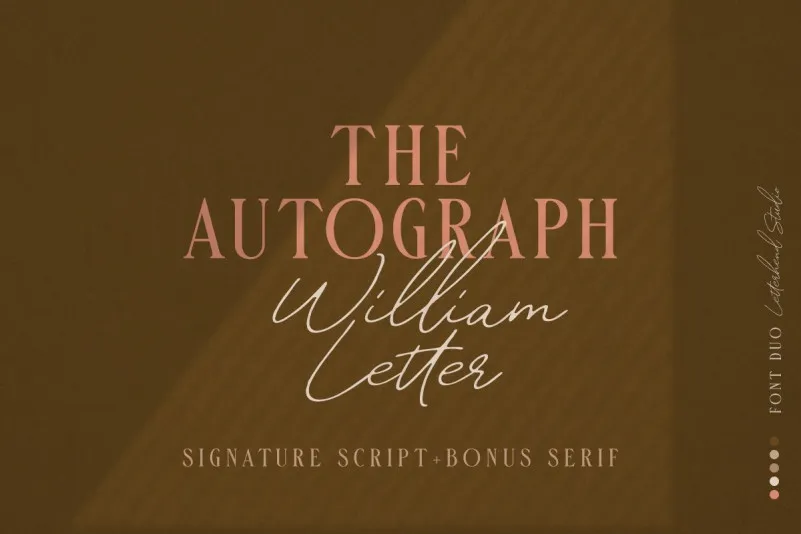
William Letter Signature Font – Download Grátis
Esta é uma fonte escrita a mão com traços elegantes e sofisticados, que combina elementos de uma script elegante com as curvas únicas e o fluxo suave do tinta, criando um estilo de assinatura moderno e natural. Introduzimos a William Letter Font. Este design foi criado pela Letterhend Studio e compartilhado para oferecer você uma perfeita combinação tipo de letra consistindo em uma assinatura e uma fonte serifada. Esta tipografia apresenta um visual elegante e limpo, que se adequa perfeitamente a diversas aplicações como headline, logotipo, roupas, convites, marca, embalagens, anúncios etc.